越境する書体デザイナーたち
誠文堂新光社は、2024年5月9日(木)に、グローバルに活躍する書体デザイナーたちを取り上げる新刊で世界で通用する発想や手法のヒントが満載の一冊「越境する書体デザイナーたち」を発売する。
文字はわたしたちの言葉を伝達する媒体として欠かせないものだが、日本語においてゴシック体や明朝体が存在するように、文字にはそれぞれの言語ごとに異なるスタイル=書体が存在する。
「越境する書体デザイナーたち」で紹介するのは、そんな文字にカタチを与える「書体デザイン」を生業にする人たち。
近年、書体デザインの世界では、異なる国や地域のデザイナー同士が協力し、複数の言語・文字で統一的なスタイルをもった多言語書体を開発する動きが活発化している。
地域固有の文化を尊重しつつ、国際的に通用するデザイン手法やコミュニケーション能力を駆使して、個人デザイナーであっても世界的な企業と協働している多言語フォントデザイナーたち。
「越境する書体デザイナーたち」では、欧州、中東、アジアなど、ラテンアルファベット圏以外の国を拠点に活動する14組の独立系書体デザイナー/ファウンドリーの書体見本とインタビューを収録し、世界で通用する発想法や手法、デザイン哲学を紹介。
彼/彼女らのグローカルな視点や思考法、制作手法には、デザイン以外でも役立つ思考や発想が詰まっているだろう。
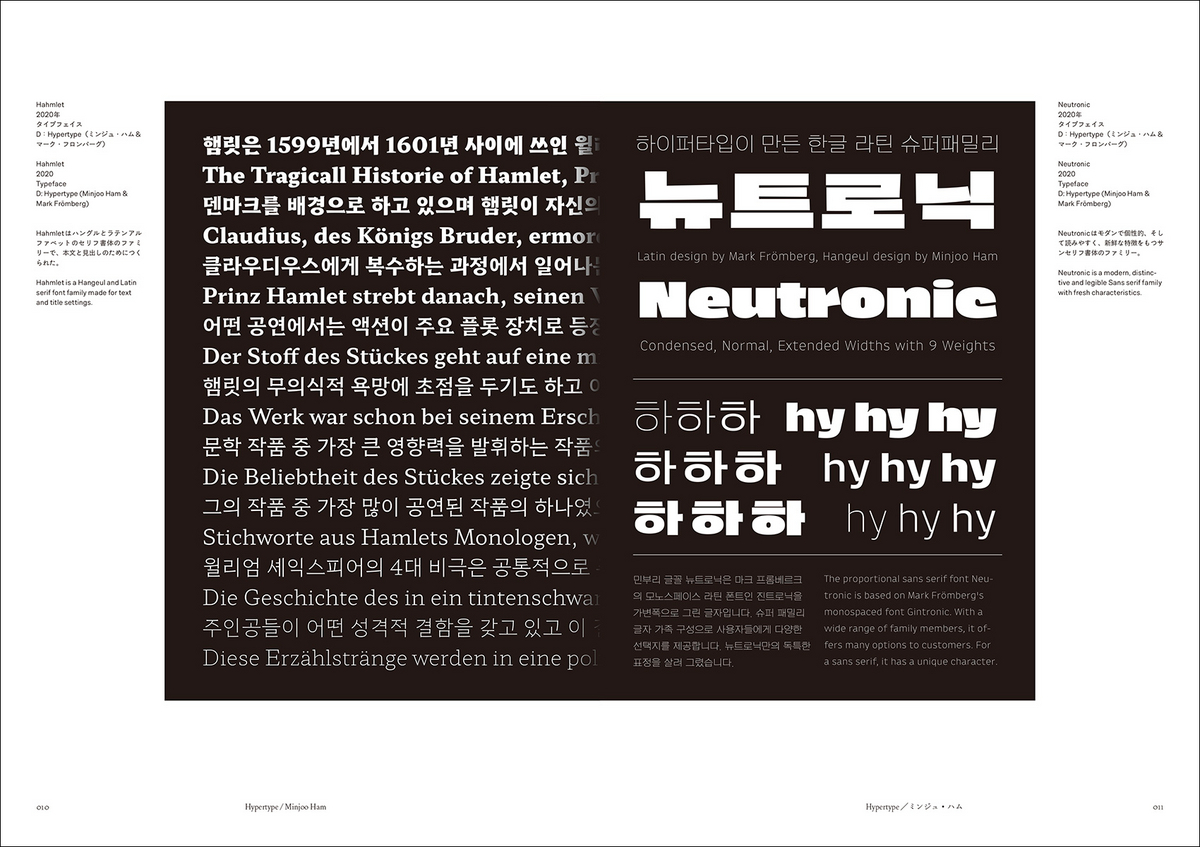
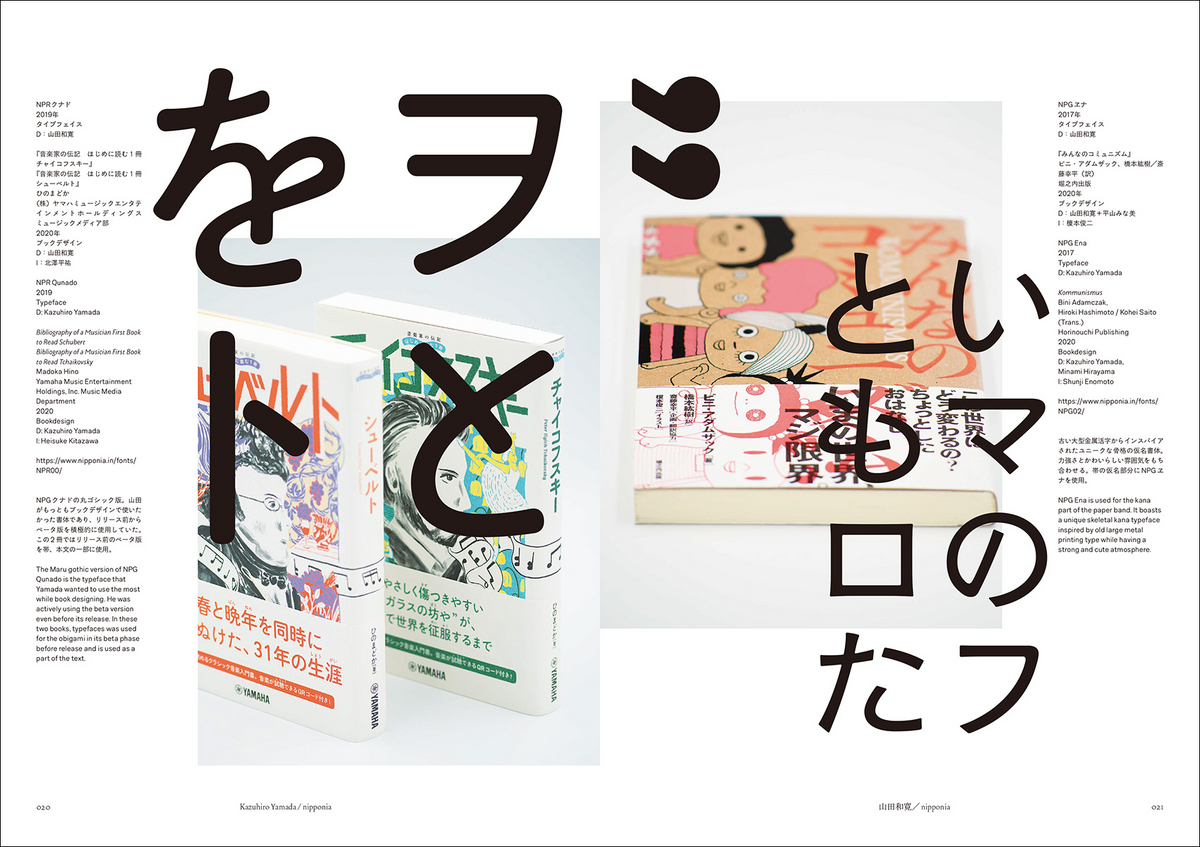
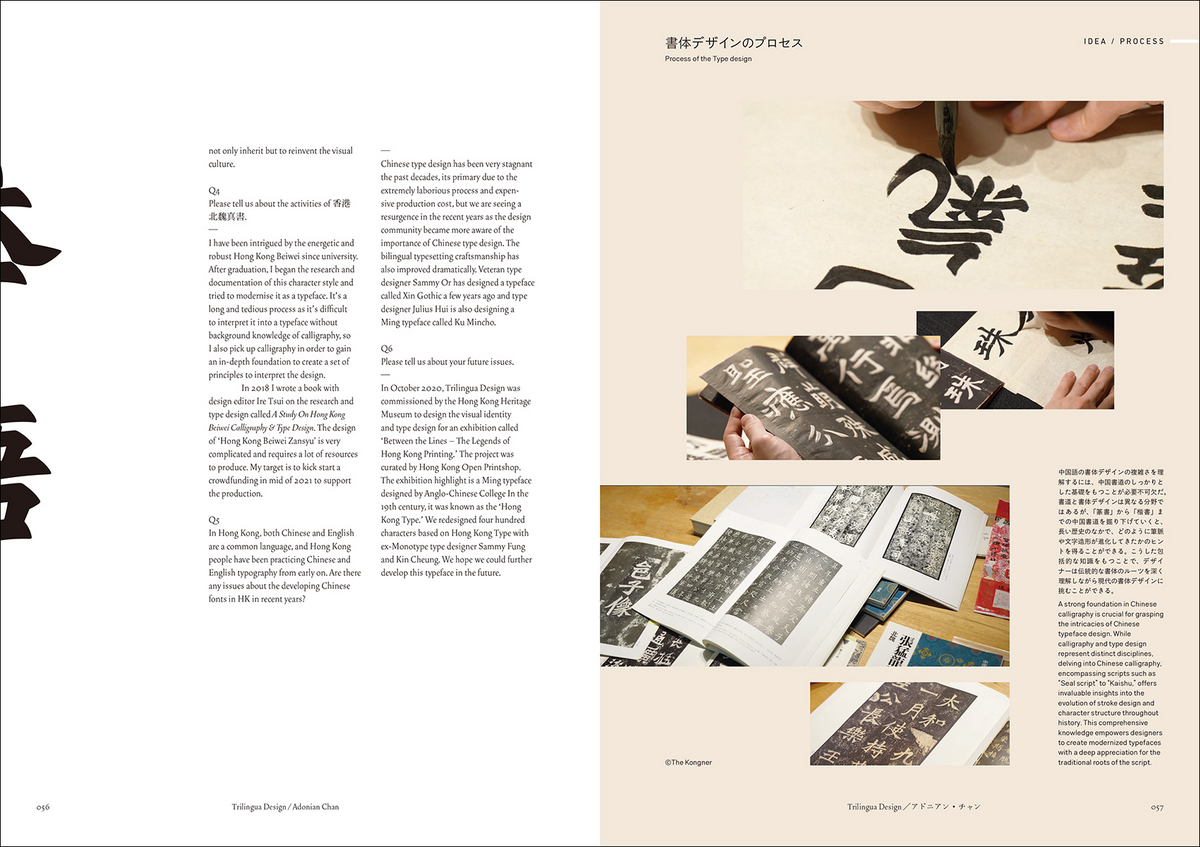
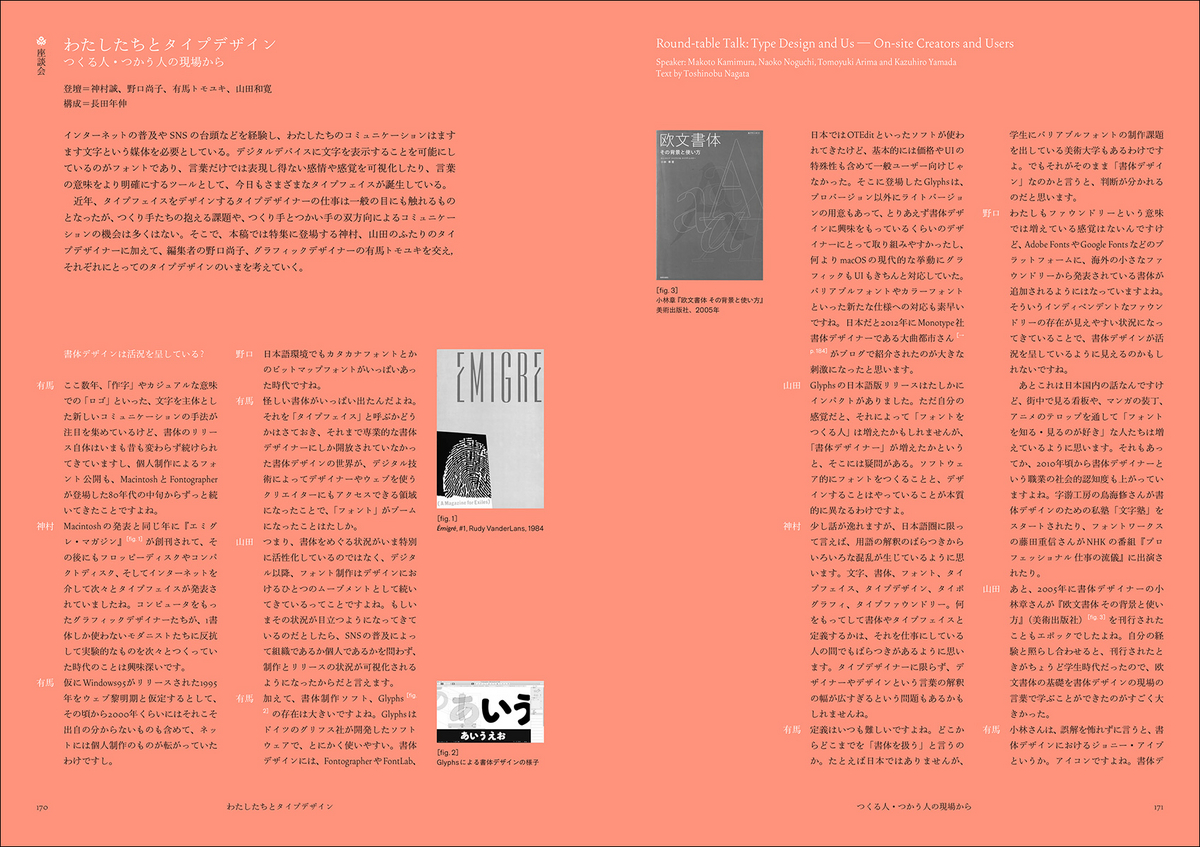
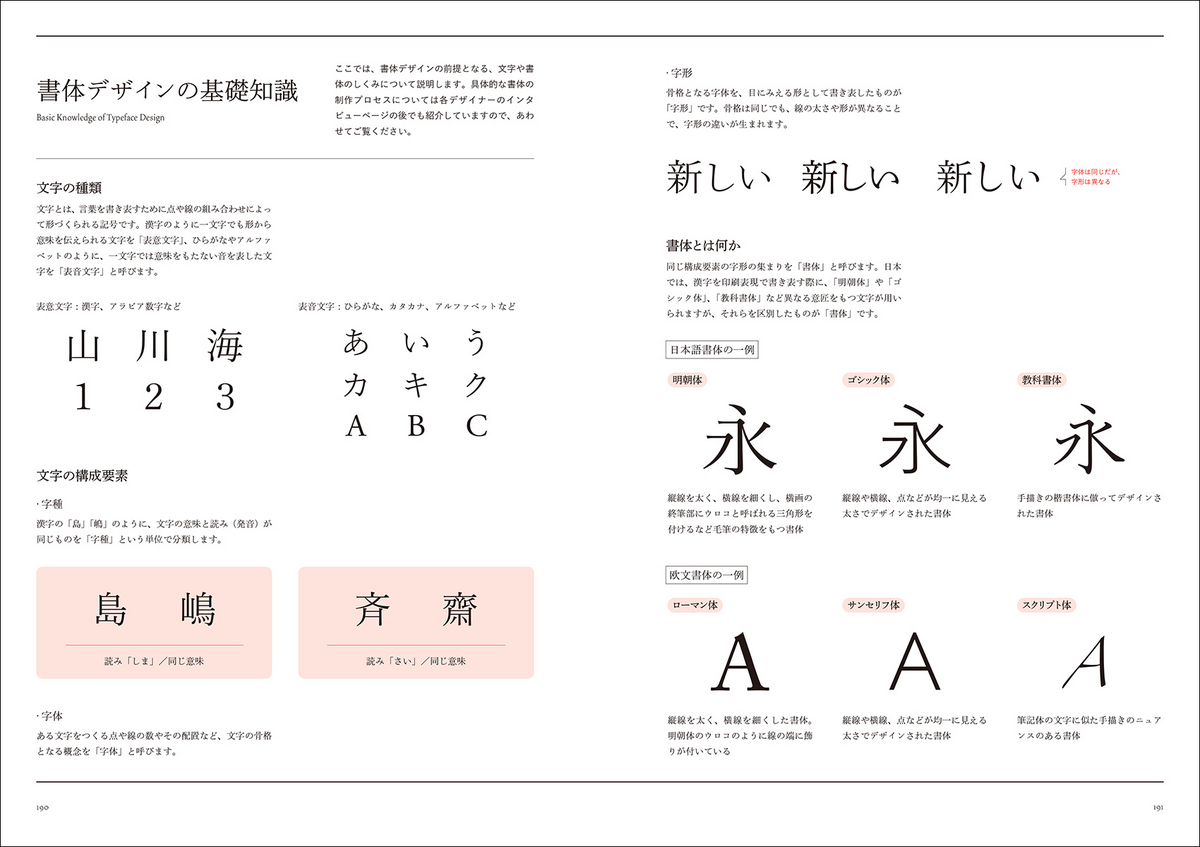
「越境する書体デザイナーたち」【目次】
アイデア392号 特集「タイプデザイン・ナウ 独立系タイプファウンドリーの実践」?イントロダクション?
【Chapter 1】独立系タイプファウンドリーの実践
・Hypertype/ミンジュ・ハム
・山田和寛/nipponia
・Detail Type Foundry/神村誠+神村さち
Śirin — Kwan/シリン・グンクロイ
・Trilingua Design/アドニアン・チャン
・Naïma Ben Ayed Bureau/ナイマ・ベン・エイド
・Briefcase Type Foundry/トマス・ブルーシル、ペトラ・ドチェカローバ、ラデック・シドゥン
・justfont
・debakir/カジャック・アペリアン ・ラディム・ペスコ/RP Digital Type Foundry
・Grilli Type
・NaN ・Kowloon Type/ジュリアス・フイ
・Maliikātype/シュエ・ティエンメン
【Chapter 2】テキスト編:タイプデザイン・ナウ
・座談会:わたしたちとタイプデザイン つくる人・つかう人の現場から
登壇:神村誠、野口尚子、有馬トモユキ、山田和寛 構成:長田年伸
・つくり手たちを支援するプラットフォームづくり
インタビュー:トラヴィス・ケッヘル、リジー・ゲルシェンゾーン(Future Fonts)
・デジタル時代の欧文書体デザインと近況
文:大曲都
・書体デザインの基礎知識
あとがき